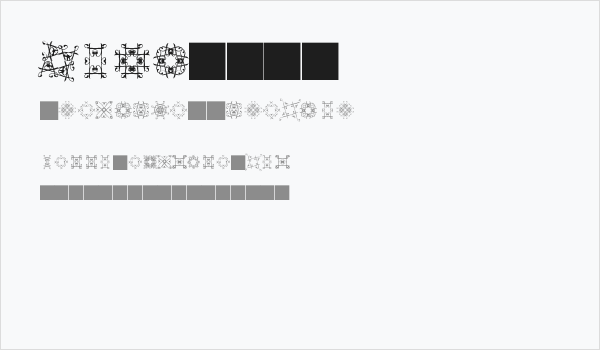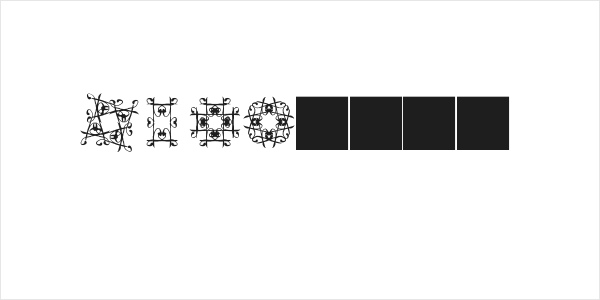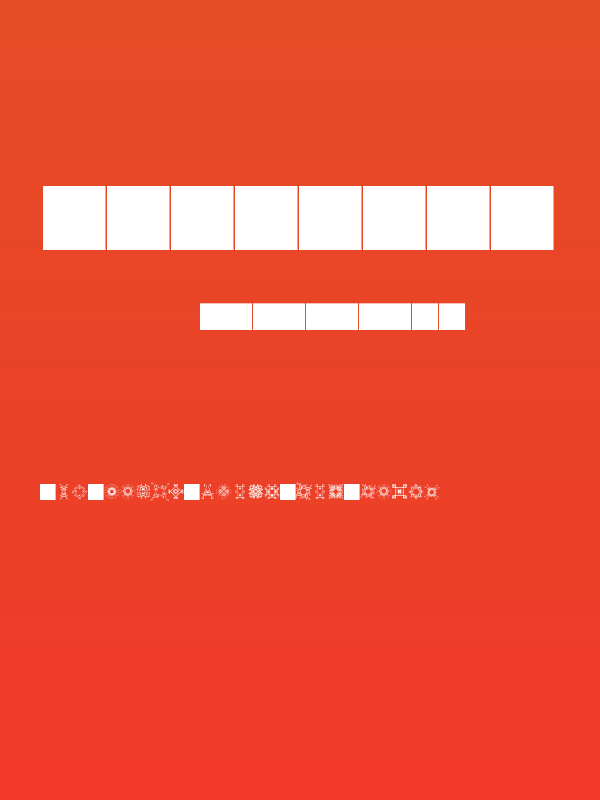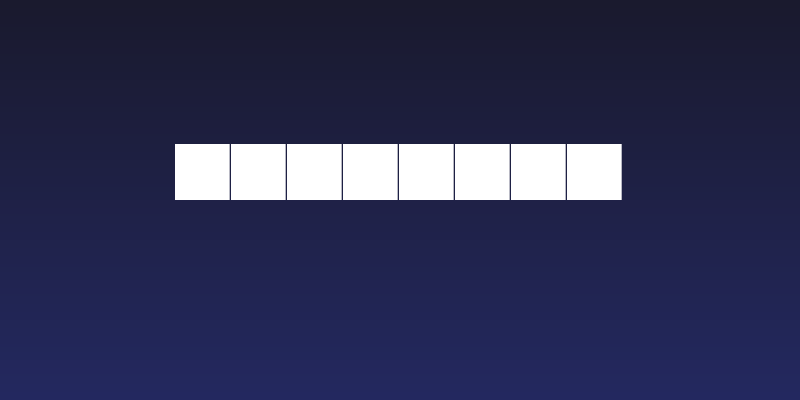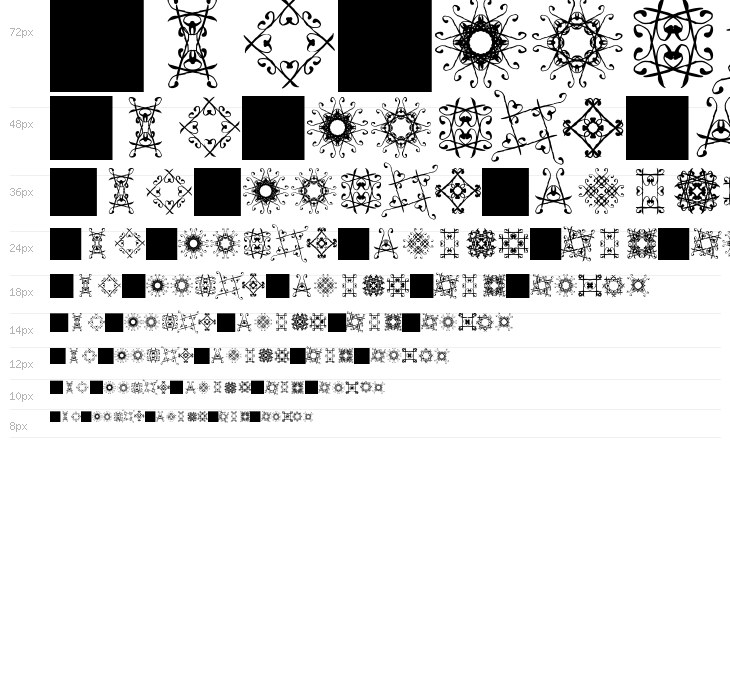
font3933 Font
✎ Dingbats
| श्रेणियाँ | Dingbats |
| कंट्रास्ट | High |
| समग्र शैली | Vintage, Decorative |
| उपयोग का मामला | Logos, Headlines, Decorative elements |
| सुझाए गए प्रोजेक्ट | Ideal for wedding invitations, luxury branding, decorative posters, and artistic projects that require a touch of elegance and sophistication. |